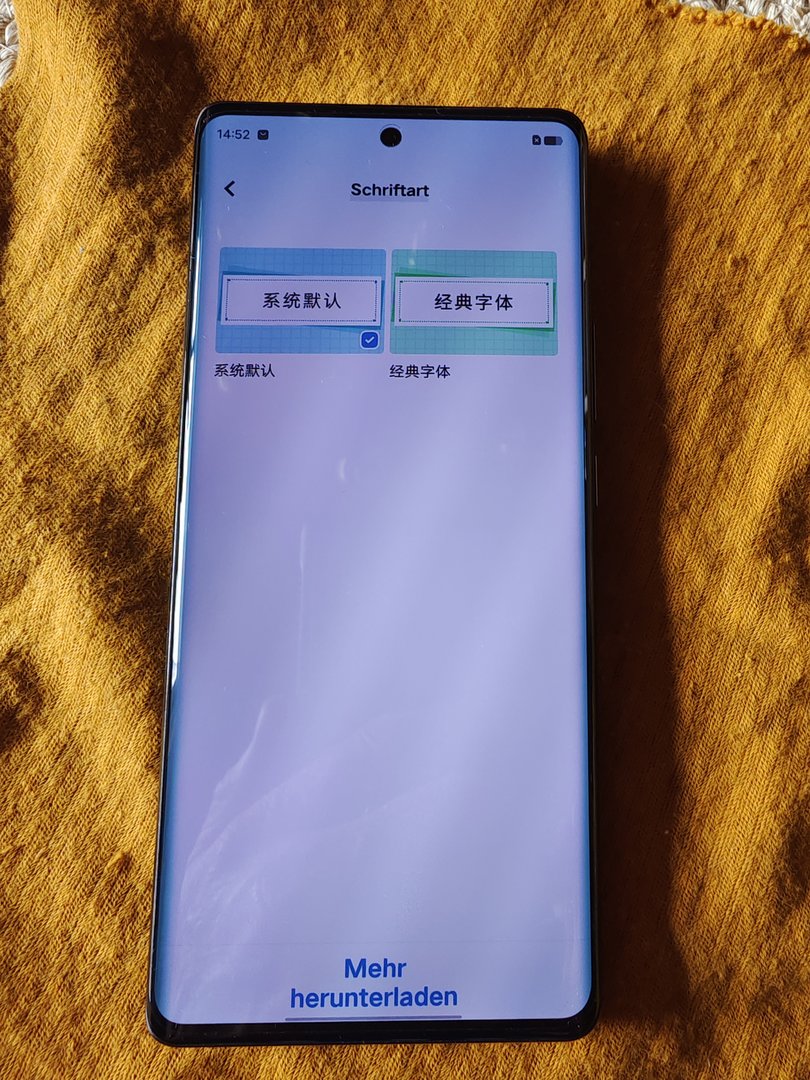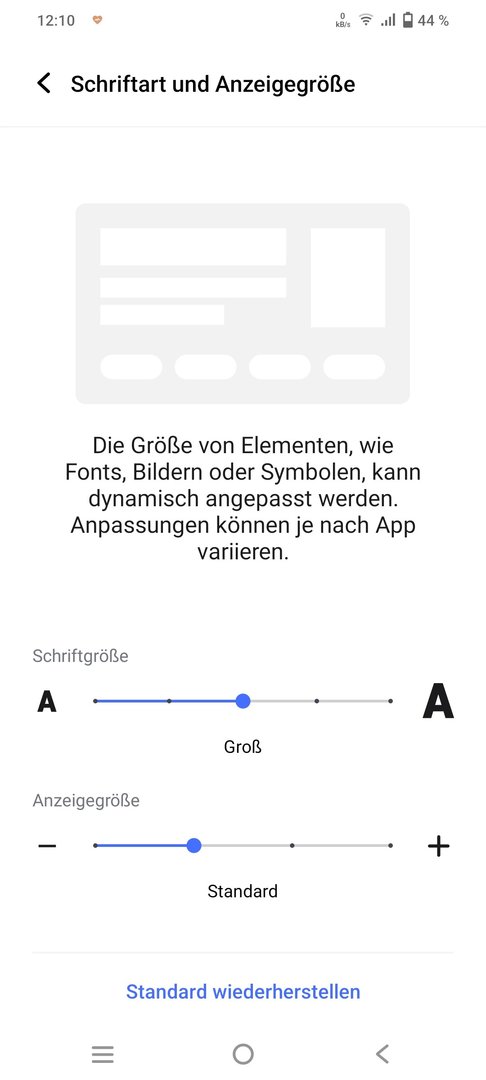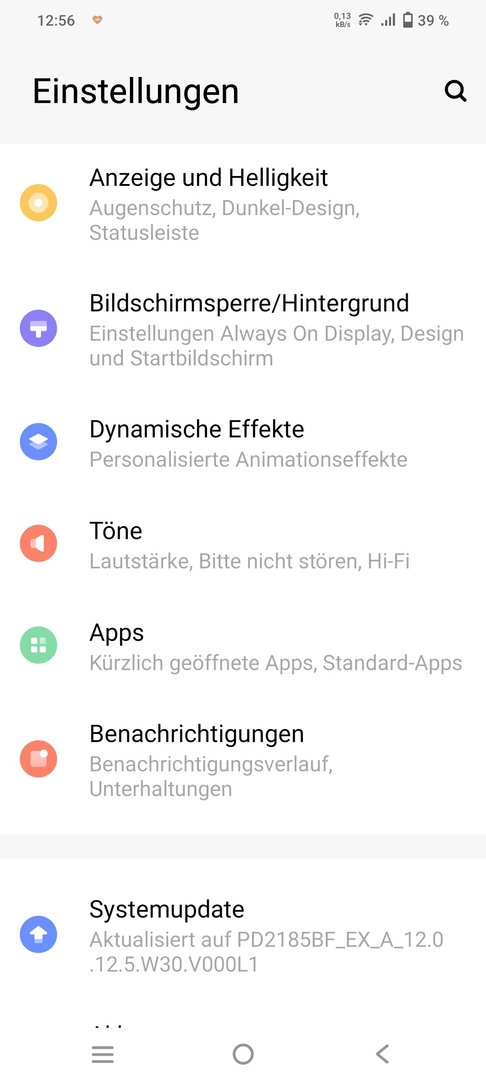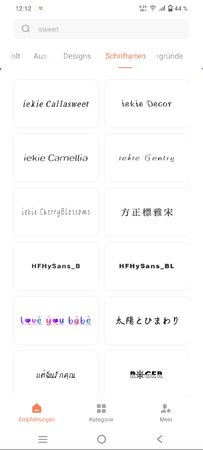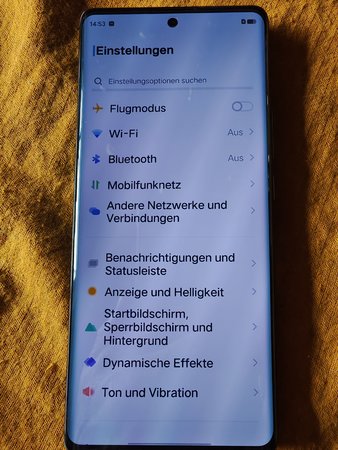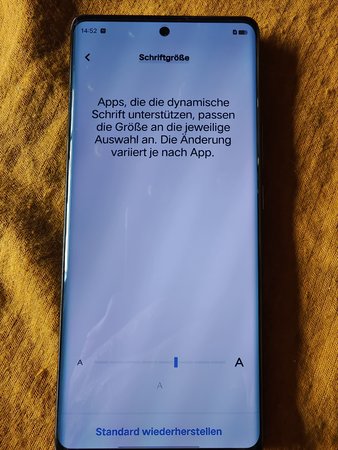
Vivo X80 (Pro Plus) Sind in Funtouch verschiedene Schriftarten für Deutsch auswählbar?
@Aschenbrenner Hallo, noch ne kurze Frage von jemand der leider nicht so gut sieht wie die meisten... Ich hatte gelesen dass beim X70 pro plus mit Origin OS die vom System bereitgestellten Schriftarten sehr dünne Buchstaben aufweisen was sich wohl auch nicht ändern lässt. Man könne wohl nur die Schriftgröße ändern...
Besteht diesbezüglich ein Unterschied in der Funtouch Version, sind dort verschiedene Schriftarten für deutsch auswählbar oder auch Fettschrift?
Ganz groß wäre es wenn du jeweils einen Screenshot der gleichen Seite des Settingsmenüs von Origin und Funtouch hochladen könntest, natürlich mit gleicher Schriftgrößeneinstellung.
Dann könnte ich einen Eindruck bekommen ob ich optisch damit zurechtkommen. Danke schonmal.
@Metronomus in Fun ist das möglich Screenshot_20220625_121040.jpg
@Aschenbrenner Aber die Schriftgröße lässt sich bei Origin auch einstellen? Oder...?
Der Unterschied ist das man bei Origin keine anderen Schriftarten auswählen kann?
Ist die Schriftart in Origin wie oft beschrieben sehr kontrastschwach und dünn?
Wie gesagt 2 Vergleichsbilder wie die Darstellung der Schriften aussieht wäre super, am Besten irgendein Bereich des Menüs mit viel Schrift wo ich den Unterschied sehen und beurteilen kann...danke dir
.... Das ist Fun das letzte Bild. Ich finde die Schrift beim Origin besser
@Aschenbrenner@Aschenbrenner welches von den Fotos ist Origin Os?
@Metronomus bisschen durcheinander... Die ersten drei
@Metronomus dir Origin ist viel heller...
@Aschenbrenner OK danke, also das einzige was Origin nicht bietet sind die unterschiedlichen Schriften wie bei Funtouch...?
@Metronomus bietet schon.... Musst halt runterladen